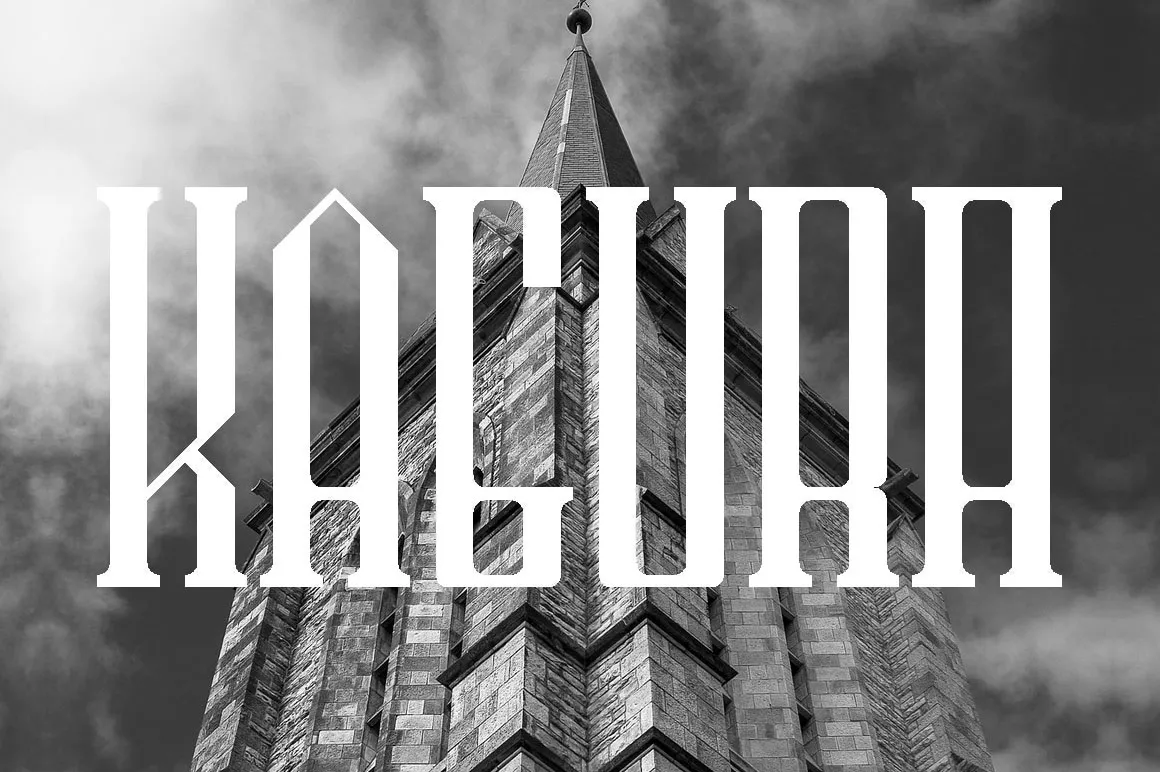
Kagura Font
Esta fonte gratuita chamada Kagura é uma escolha ideal para designers que buscam um estilo moderno e atraente para seus projetos. Crie designs incríveis com sua disposição vibrante e características exuberantes, perfeita para gráficos de tela cheia ou materiais de marketing digital. Concebida pelo designer Hamilton, a Kagura é uma fonte do tipo Display, que destaca-se por suas linhas dinâmicas e traços distintos. Ela oferece um toque único e criativo ao seu design, seja em materiais impressos ou online. A sua personalização permite explorar diferentes estilos de escrita e tonalidades, tornando-a uma fonte versátil que se adapta a muitas ocasiões. Descarregue Kagura agora e tenha à disposição um recurso gráfico único e de alta qualidade. Não perca essa oportunidade para dar um toque especial aos seus projetos.